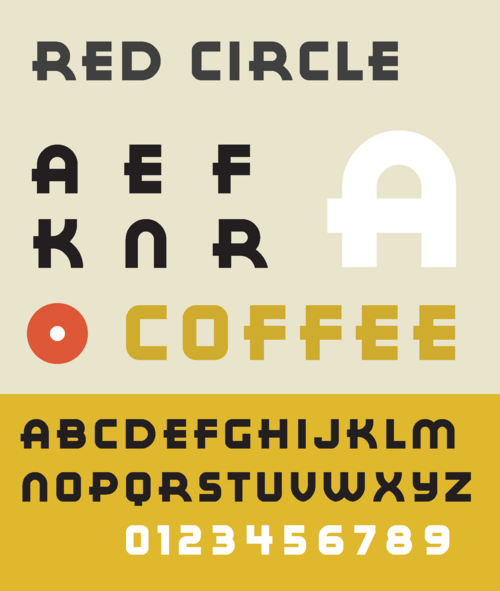
| カテゴリ | サンセリフ |
| 分類 | 幾何学的サンセリフ |
| デザイナー | ハロルド・ローナー |
| 鋳造所 | ハロルドフォント |
| リリース日 | 2006 |
Red Circleは、 Harold Lohnerによってデザインされた幾何学的なサンセリフ書体で、 A&P のEight O'Clock、Red Circle、Bokarブランドのアラビカコーヒー豆のパッケージや広告に使用された 1930 年頃のレタリングに基づいています。
Red Circle は、アールデコ時代の幾何学的探求を示す大文字の書体です。全体的に直線的な構造ですが、A、B、D、M、N、 Rの文字では円形が目立っています。このレタリングは、Georg Trump のCity書体と比較できます。A 、B、E、H、K、P、 Rの文字では、外側の角が丸く、横線がステムの左側まで伸びています。文字MとNは、 Herbert Bayer の1927 年の実験的なユニバーサル書体Architype Bayerの同じ文字に似た、カロリング小文字のmとnの形をしています。